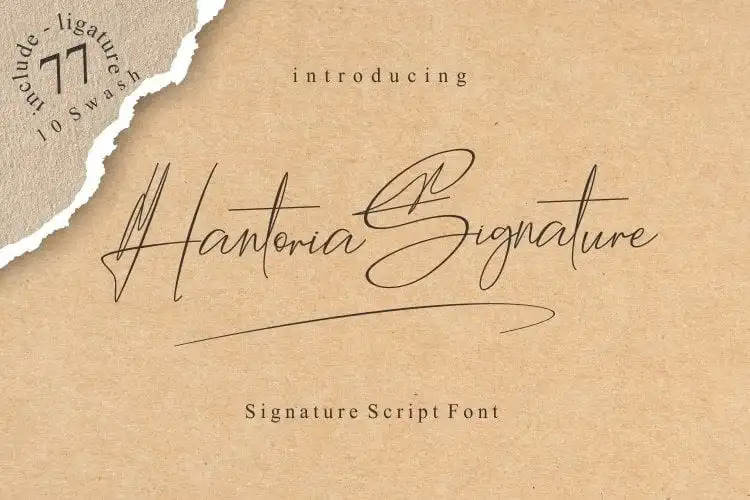
Hantoria Signature Script Font – Download Grátis
A Hantoria Signature Script Font é uma opção perfeita para projetistas que desejam criar designs com um estilo natural e autêntico, inspirado na escrita a mão real. Seu uso vai transformar seus trabalhos de modo impecável, proporcionando um toque refinado que traduz a arte manual. Desenvolvida pelo designer Eknoji no site 99designs, essa fonte oferece uma versatilidade impressionante para diversas aplicações: desde logotipos e identidades visuais até convites de casamento e embalagens de produto, passando por posts nas redes sociais, anúncios e até mesmo marcas digitais. Ideal tanto para elementos visuais como também para design gráfico, a Hantoria Signature é o elemento que adiciona aquele toque especial ao seu trabalho. Perfectly suited for creatives looking to add that personal touch with a handwritten aesthetic without having to handwrite every element themselves, esta fonte se torna um aliado inestimável em qualquer projeto de design gráfico.